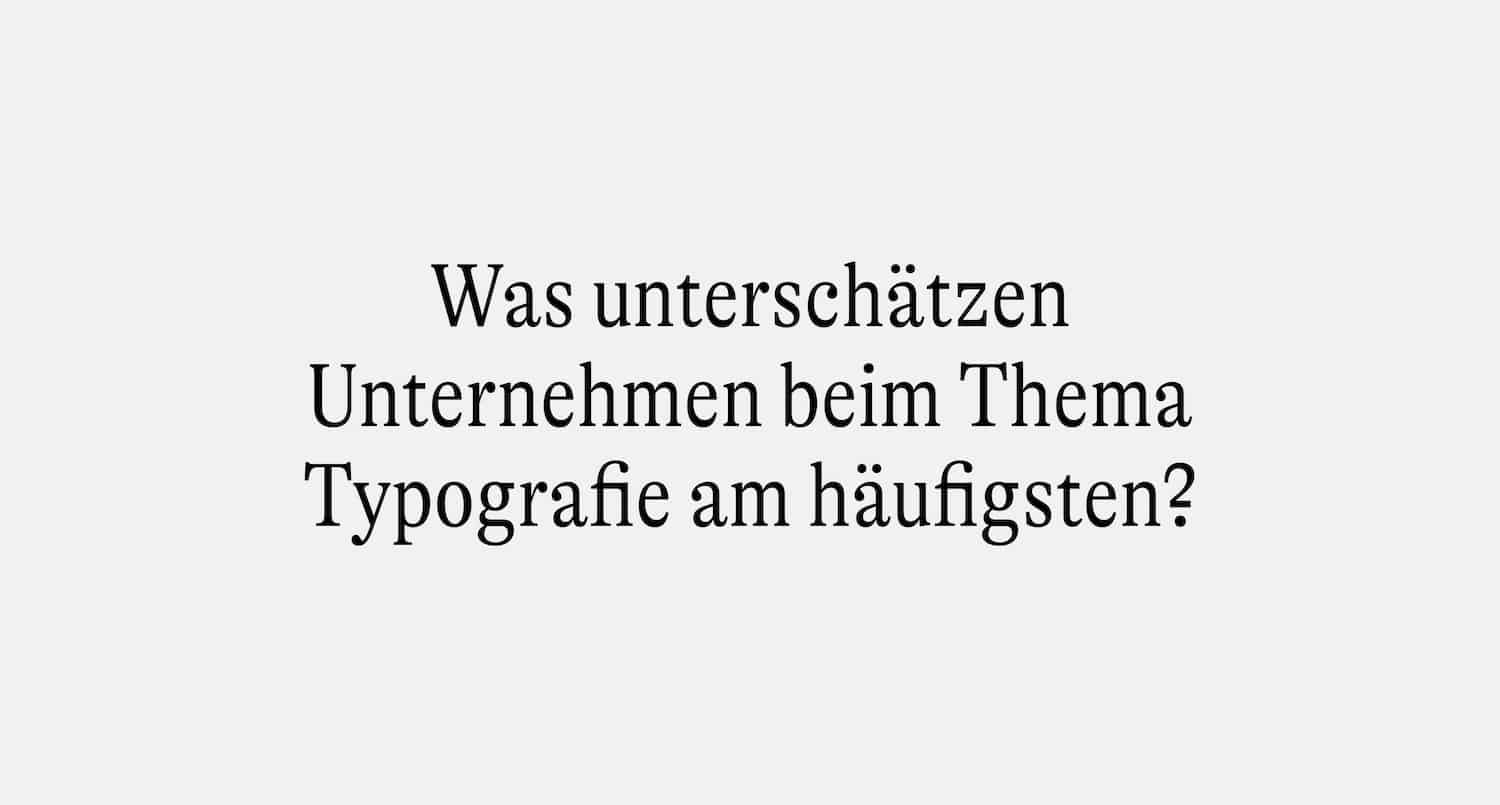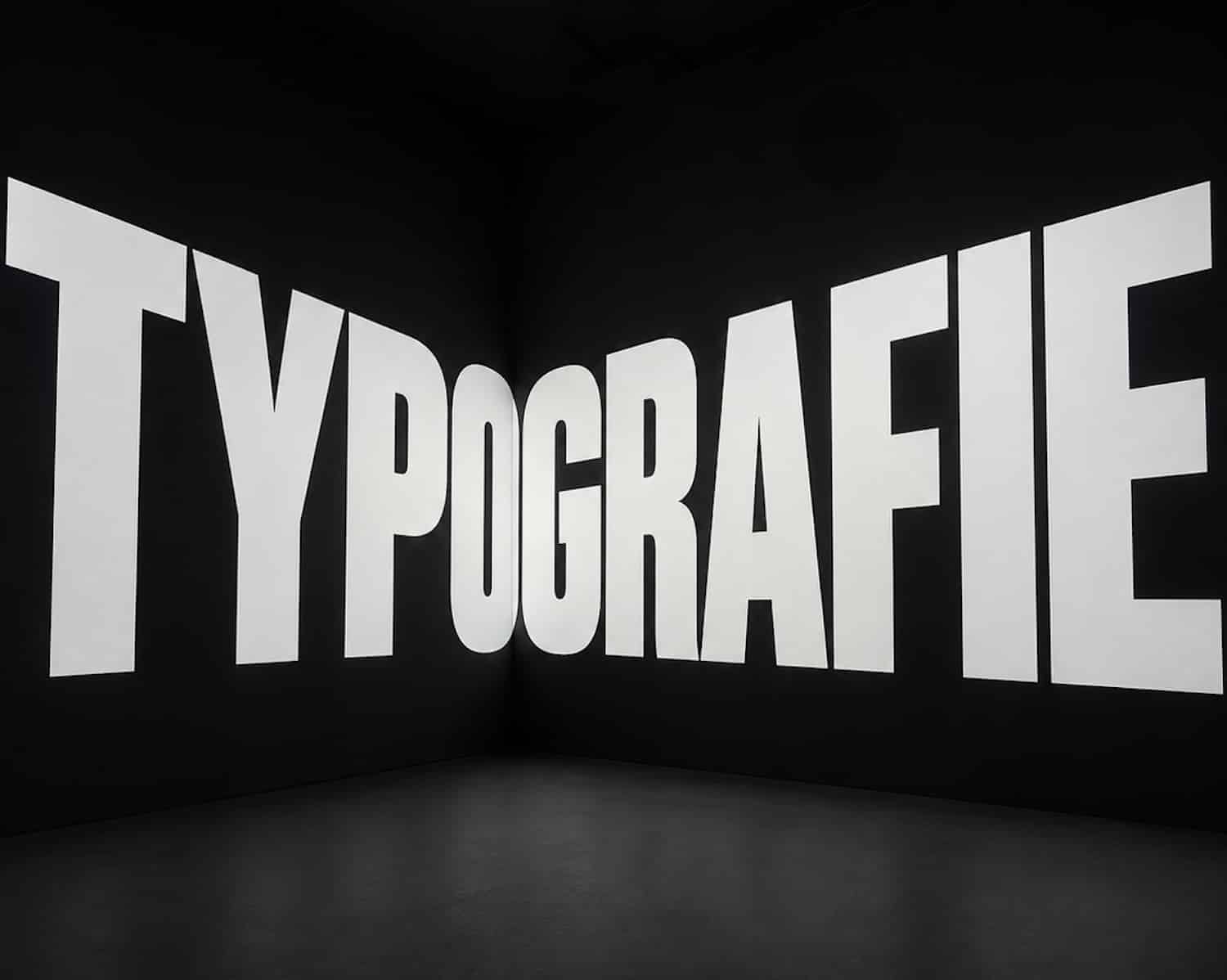
Was Unternehmen beim Thema Typo unterschätzen
Unterstützt von der Typographischen Gesellschaft München e.V. befragte der Designer Patrick Marc Sommer 20 Kreative zu diesem Thema – mit spannenden Ergebnissen.
Im August und September 2026 beantworteten 20 Menschen aus Typografie, Gestaltung, Kommunikation, Lehre und Unternehmenspraxis schriftlich dieselbe offene Frage: Was unterschätzen Unternehmen beim Thema Typografie am häufigsten und welche Folgen hat das? Die Umfrage ist qualitativ angelegt und nicht repräsentativ. Sie zeigt persönliche Einschätzungen, fachliche Positionen und Erfahrungen aus der Praxis.
Die neue Hausschrift ist ausgewählt. Sie passt zur Strategie, unterscheidet sich vom Wettbewerb und sieht auf den Präsentationsfolien hervorragend aus. Eigentlich könnte das Designteam zufrieden sein. Eigentlich.
Denn eine Hausschrift hat zwei Leben. Das erste beginnt in der Präsentation. Dort steht sie in sorgfältig gesetzten Headlines, aufgeräumten Musterseiten und neben dem neuen Logo. Sie wirkt eigenständig, präzise und unverkennbar. Alles ist unter Kontrolle. Das zweite Leben beginnt am nächsten Morgen. Jemand öffnet PowerPoint. Eine Agentur setzt den Geschäftsbericht. Die IT prüft die Installation der Schriftdateien. Ein E-Mail-Programm verwendet eine Ersatzschrift. In einer internationalen Anwendung fehlen Zeichen. Bei einem externen Dienstleister sieht dieselbe Datei plötzlich anders aus.
Eine passende Schrift auszuwählen bleibt wichtig. Entscheidend ist, aus ihr ein System zu machen, das unter realen Bedingungen funktioniert.
Eine redaktionelle Auswertung zeigt die Gewichtung: 15 der 20 Befragten sprechen über Markenidentität, Wiedererkennbarkeit oder Wirkung. Neun thematisieren Implementierung, Technik, Lizenzen oder Zuständigkeiten. Vier stellen Lesbarkeit, Orientierung oder Barrierearmut in den Mittelpunkt. Die Kategorien überschneiden sich. Trotzdem wird eine Lücke sichtbar: Über Wirkung wird häufiger gesprochen als über die Bedingungen des Alltags.
Schrift ist überall
»Schrift ist sichtbare Sprache«, schreibt Erik Spiekermann. Fast alles, was Unternehmen erklären, versprechen, verkaufen oder dokumentieren, wird irgendwann gelesen. Typografie gibt dieser Sprache eine Stimme.
Noch bevor Leser:innen den Inhalt vollständig erfassen, nehmen sie Form, Rhythmus, Dichte und Proportion wahr. Eine Marke wirkt kompetent oder beliebig, offen oder abweisend. Manuel Kreuzer formuliert es so: Typografie transportiert nicht nur Information, sondern »erzeugt« selbst Bedeutung.
»Viele Unternehmen unterschätzen noch immer, wie wichtig Schriften für einen einheitlichen Auftritt sind.«
Daniel Perraudin, Schriftdesigner, Gallery Type
Das macht Schrift zu einem Brand Asset. Jan Erlinghagen beobachtet allerdings, dass sie in Unternehmen häufig eher als etwas gilt, »das man halt zum Lesen braucht«. Dabei kann ihr Wiedererkennungswert ähnlich groß sein wie der eines Logos. Daniel Perraudin nennt Mercedes-Benz als Beispiel: Die Schrift könne selbst ohne den Stern als Absender funktionieren, bis hinunter zum Smartwatch-Display.
Die Realität steht nicht im Manual
Viele Designmanuals zeigen eine Headline, einen kurzen Fließtext und eine einfache Tabelle. Die Wirklichkeit ist selten so übersichtlich.
Katharina Marx lenkt den Blick auf den Geschäftsbericht. Ein Lagebericht oder Anhang benötigt fünf bis sieben Überschriftenebenen. Dazu kommen komplexe Tabellen und Grafiken. Eine Eigenkapitalveränderungsrechnung lässt sich nicht sinnvoll mit den Regeln einer kleinen Mustertabelle ordnen. Wer hier nur formal korrekt gestaltet, kann inhaltlich scheitern.
Michael Wörgötter unterscheidet zwischen »lesbar machen« und »erkennbar machen«. Das erste ist für ihn das wichtigere. Text brauche Struktur, Ordnung und Orientierung. Julia Wittich beschreibt die Folgen schlechter Typografie in Begriffen, die auch Auftraggeber:innen verstehen: höhere kognitive Belastung, mehr Verständnisfragen, zusätzlicher Supportaufwand, geringere Conversion und eine schwächere Markenwahrnehmung.
Gute Typografie gibt einer Marke also nicht nur einen eigenen Ton. Sie hilft Menschen, Informationen schneller zu erfassen. An den unauffälligen Stellen zeigt sich, ob ein System gestaltet wurde oder nur ein Look.
Was ein Font können muss
Eine Schrift kann hervorragend zur Markenpersönlichkeit passen und für die geplanten Anwendungen trotzdem ungeeignet sein. Vor der Entscheidung lohnt sich deshalb ein Blick jenseits der schönen Musterwörter.
Welche Sprachen werden benötigt? Enthält die Familie Tabellenziffern und genügend unterscheidbare Schnitte? Sind Sonderzeichen und Währungszeichen vollständig? Welche OpenType-Funktionen und Dateiformate stehen zur Verfügung? Gibt es eine Fallback-Schrift für Office und E-Mail?
»Typografie nicht nur Gestaltung ist, sondern Infrastruktur für ihre Markenstimme«
Friedrich Althausen, Creative Type Director bei Monotype
Wer erst bei Geschäftsberichten, Rechnungen oder internationalen Anwendungen feststellt, dass wichtige Funktionen fehlen, hat zu früh vor allem auf den Charakter geschaut. Eine gute Schriftentscheidung beginnt beim tatsächlichen Einsatz.